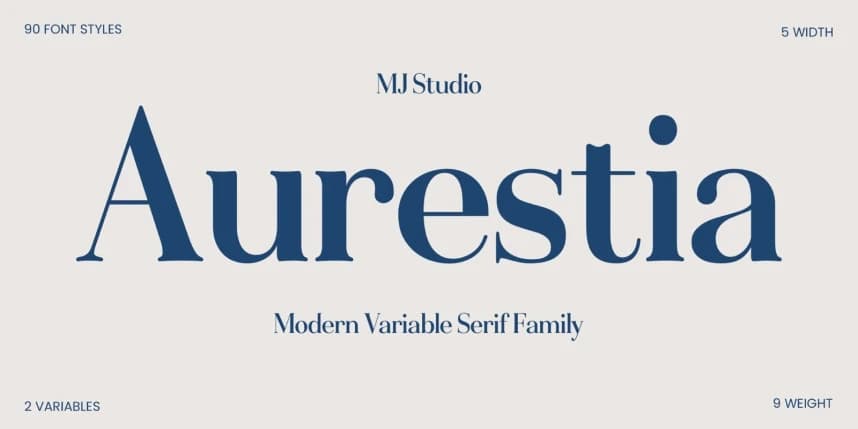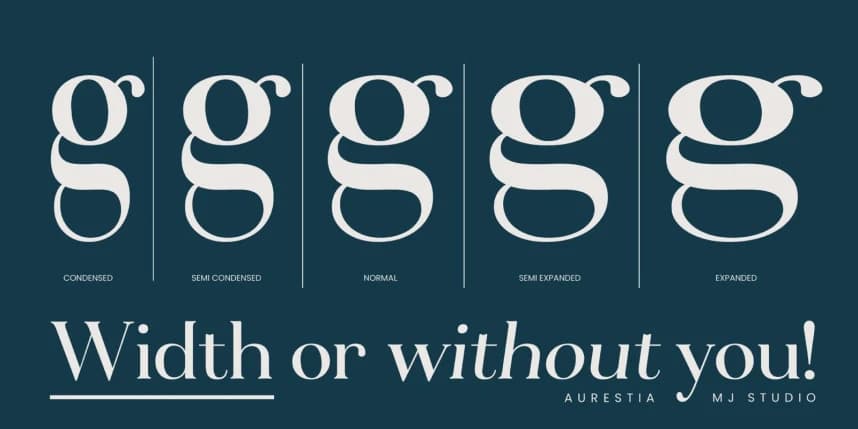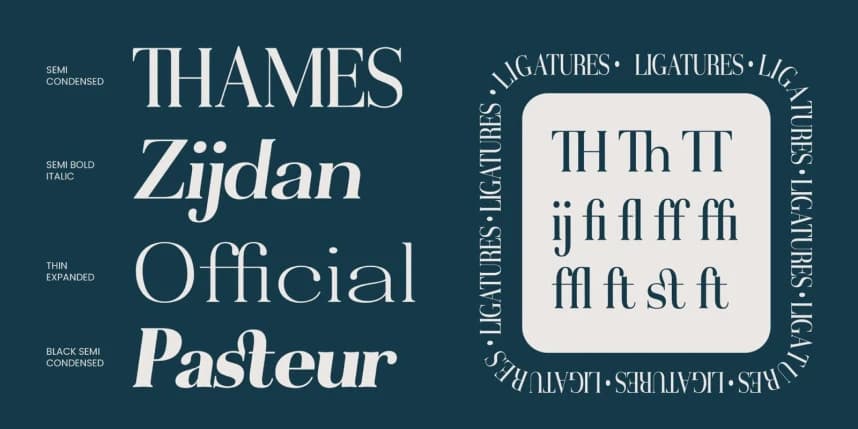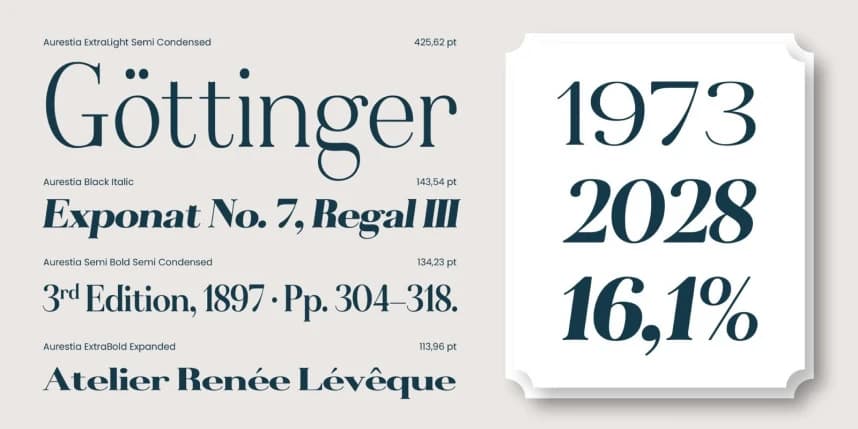
Aurestia Font Family
Aurestia Font Family – Modern Variable Serif Family Aurestia, klasik zarafet ile çağdaş esneklik arasında mükemmel dengeyi sunmak için tasarlanmış modern bir serif yazı tipidir. İncelikli harf biçimleri, zarif oranlar ve özenle tasarlanmış serif detaylarıyla.
Aurestia Font Family – Modern Variable Serif Family Aurestia, klasik zarafet ile çağdaş esneklik arasında mükemmel dengeyi sunmak için tasarlanmış modern bir serif yazı tipidir. Geliştirilmiş harf biçimleri, zarif oranlar ve özenle tasarlanmış serif ayrıntılarıyla.